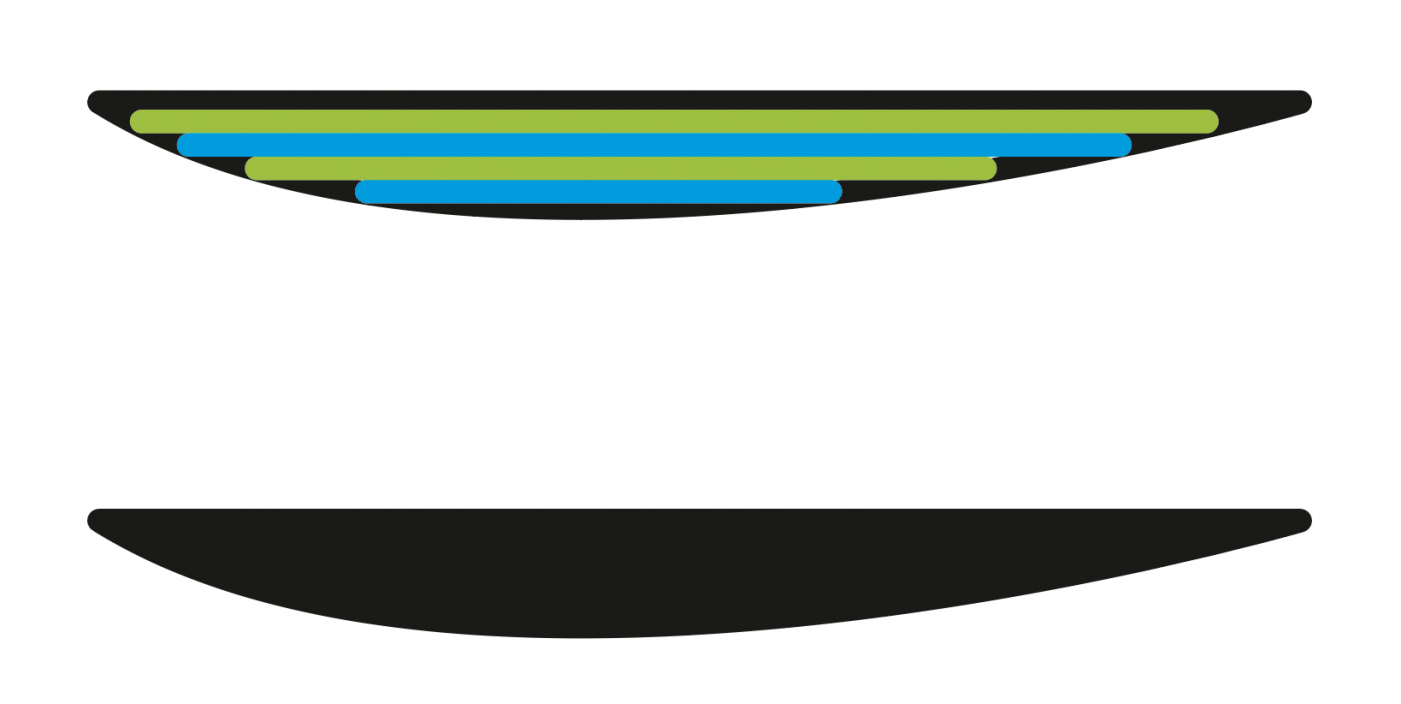
Nachdem ich vor einiger Zeit eine Kopier- und Graviermaschine erstanden habe - eigentlich hauptsächlich zum Fräsen und Kopieren von Modellen - möchte ich jetzt doch gerne auch mal das Gravieren von Schriften ausprobieren.
Hier ein Beispiel einer solchen Maschine:
Ein paar Schriftschablonen gabs zu der Maschine dazu. Die Schriften sind jedoch recht langweilig. Sieht nach irgendwelchen DIN-Schriften oder ähnlichem aus. Sie haben nur eine gleichbleibende Strichstärke und sind sehr technisch und ökonomisch gestaltet. Beispielsweise sind in Buchstabensätzen, die richtigherum sowie spiegelverkehrt vorhanden sind (Braucht man im Formenbau, weil Formen meist spiegelverkehrt gebaut werden), symmetrische Buchstaben, wie A, V, W, X, Y, I, ... nur einmal vorhanden und müssen für beide Sätze verwendet werden. Man hat also scheinbar auf jegliche asymetrische Gestaltung verzichtet, die dazu führen würde, daß eine Buchstabe in zwei Schablonen angefertigt werden müsste.
Gibt es hier vielleicht jemanden der sich mit Gravur-Schriften auskennt? Mich würden grundsätzlich Kataloge mit Schriftsammlungen interessieren. Auch ob es Gravurschriften mit verschieden starken Linien gibt und mit welchen Techniken man die fräst. Frakturschriften wären auch sehr interessant. Allerdings sehen die meist nicht so toll aus, wenn sie nur eine Strichstärke haben.
Grundsätzlich kannst du alles gravieren, was nicht die Dickes des Fräskopfs unterschreitet.
Am einfachsten sind die Einlinienschriften mit gleichbleibender Strichstärke, da mit bereits 1 Durchlauf der Buchstabe fertig gefräst ist. Mehrlinige Schriften benötigen entsprechende mehrere Durchläufe (meist 2–8), einmal außen rum für die Kontur und mit weiteren Fräserbahnen den Buchstaben ausheben. Damit können alle Arten von Schriften graviert werden, Mindestgröße und -dicke wie gesagt vom eingesetzten Fräskopf abhängig.
Vielen Dank! Bei den Schriften im Link wird meist die Kontur gefräst und ggf. noch Linien im Inneren der Flächen. Ganzflächige Ausfräsungen sind wohl nicht üblich? Oder gibt´s die nur bei "Urwtype" nicht?
Stellenweise haben die Schriften auch unterschiedliche Strichstärken. Ich nehme an, das wird durch unterschiedlich tiefes Eintauchen des Stichels erreicht...
Weiß jemand ob´s auch irgendwo ältere Kataloge für Gravurschriften online zu betrachten gibt?
Hier findest du beispielhafte Abbildungen:
Gravierbar ist wie gesagt alles – vorausgesetzt, der Fräskopf ist fein genug fürs Motiv oder das Motiv ist groß genug für den Fräskopf.
Die unterschiedlichen Strichstärken werden nicht durch unterschiedlich tiefes Eintauchen des Fräskopfs erstellt, das ergäbe Löcher im Material, sondern durch mehrliniges Fräsen. Erst die Kontur (schwarz), dann die Strichstärke ausheben (4 Linien, blau und grün gekennzeichnet), ergibt die untere Form.
Die unterschiedlichen Strichstärken werden nicht durch unterschiedlich tiefes Eintauchen des Fräskopfs erstellt, das ergäbe Löcher im Material
Kommt auf die Materialdicke und an und wie sehr die Strichstärken unterschiedlich breit sind - oder?
Ich denke, eine Schrift wie die "Sans Humanistic 1-line " bei Urwtype könnte man schon durch verschieden tiefes eintauchen mit einem spitzen Stichel gravieren. Oder lieg ich da falsch?
Die von Dir gezeigte Graviertechnik wird dann vermutlich mit einem zylindrischen Fräser gemacht. Ich bin bisher von spitzen Fräsern ausgegangen.
Graveur bin ich nicht, aber seit 30 Jahren mit der Produktion von allerlei Druck- und anderen Erzeugnissen und befasst. Da lernt man so allerhand kennen ;-). Maschinengravuren finden nur mit der Fräse statt. Die Werkzeuge sind dabei nicht zylindrisch, sondern an der Spitze kegelförmig mit verschiedener Winkelung. Auch wenn sie gern mal "Gravierstichel" genannt werden, sind sie doch rotierend und spanend und somit eine Fräse. Innerhalb eines Buchstabens kommt dabei immer die gleiche Frästiefe zum Einsatz.